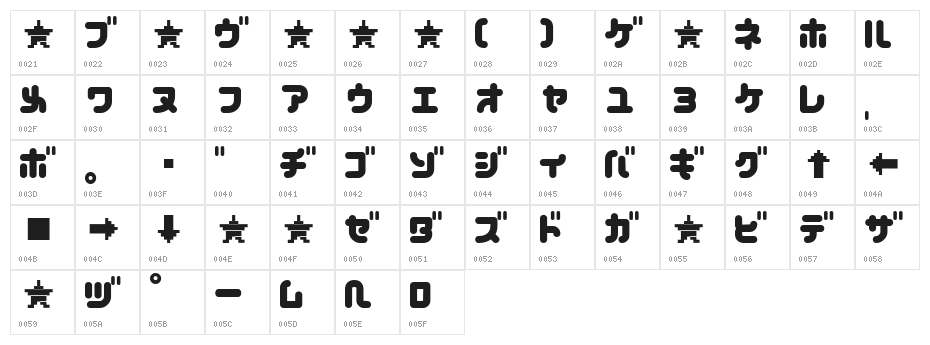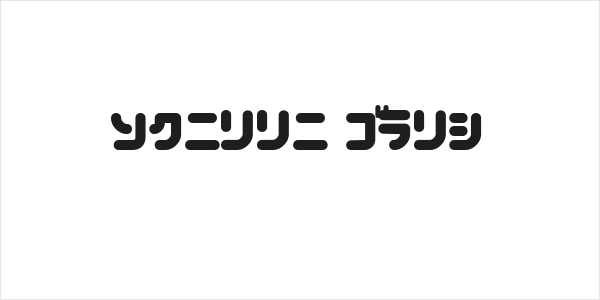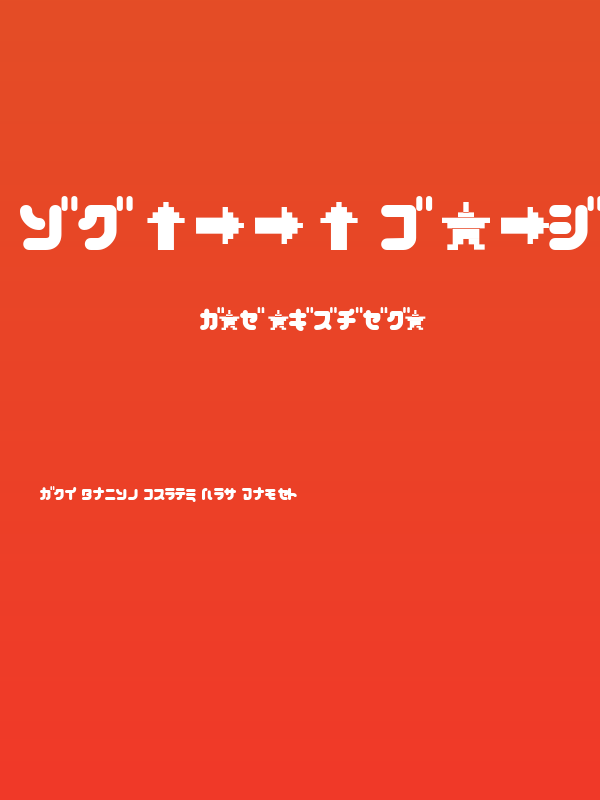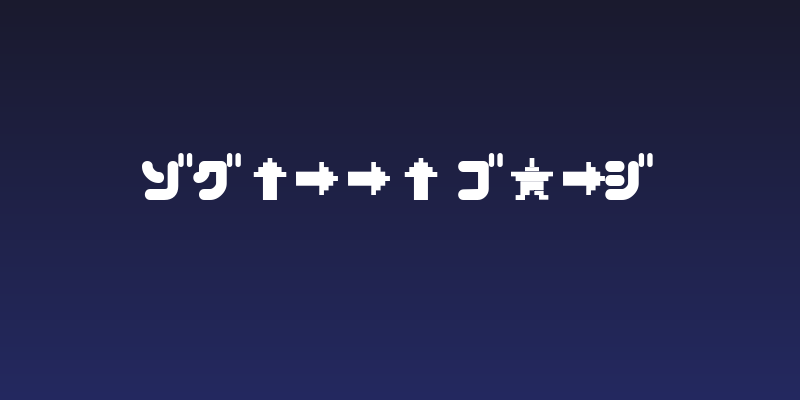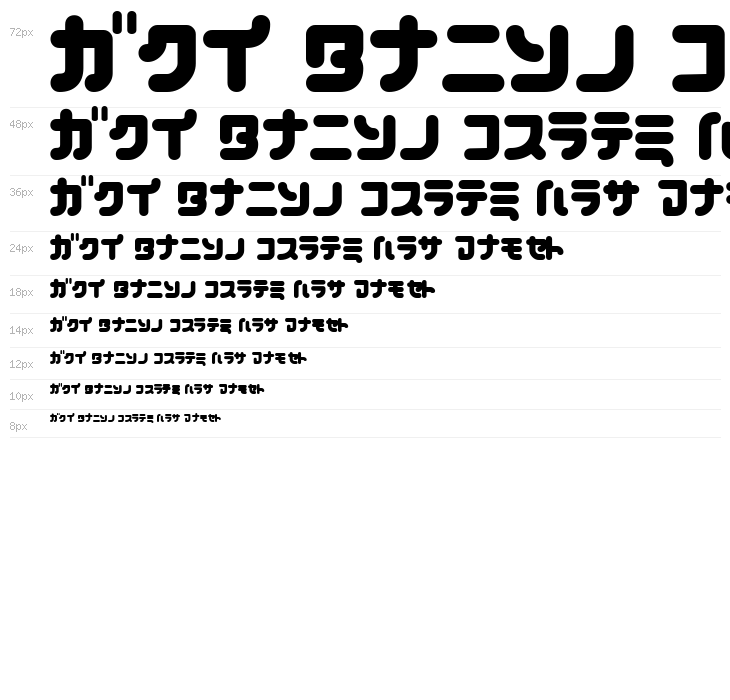
chilli Bold Font
| الاسم | chilli Bold |
| الوزن | Bold |
| النمط العام | Modern, Playful |
| مشاريع مقترحة | Ideal for children's books, playful branding, posters, and creative digital content. |